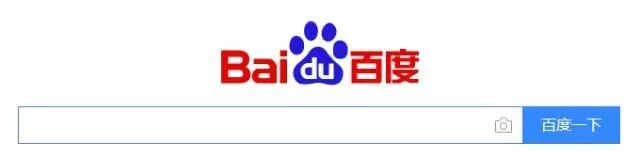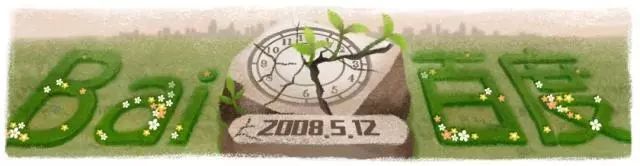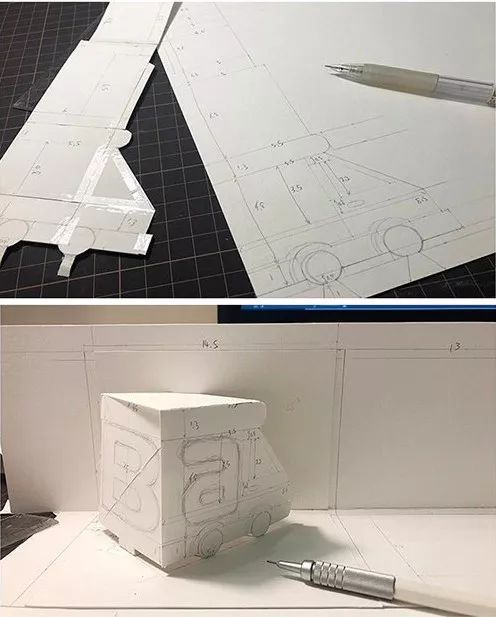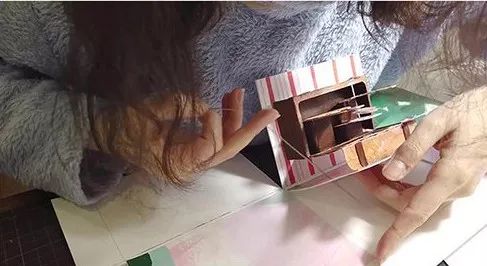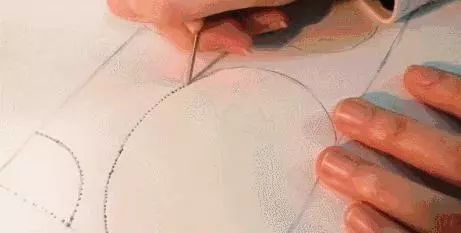
不要只盯着谷歌,百度的Doodle,同样精彩!
不要只盯着谷歌Doodle看,
多关注一下百度,
百度Doodle同样精彩!
说起谷歌,必须要说到谷歌Doodle。每到特定的日子,五花八门的Doodle总是能成为人们津津乐道的话题。
Doodle用动画的方式,各种形式串联,简单通俗来表达,谷歌作为搜索引擎存在的意义。趣味横生,已融入了生活中的方方面面。
但是对于中国网民来说,最常接触到的,其实是百度。每次打开搜索引擎的时候,你有没有留心观察过百度Doodle?下面小编带您挖掘百度有趣的Doodle和这些Doodle背后的故事~
精彩的百度Doodle
平时打开百度首页,都能看到这个熟悉的红蓝标:
也许你早有发现,在一些特别的日子里,经典的红蓝标志也会变身为各式各样的 Doodle!
下面我们一起来看看,在最近两年,百度都换过哪些好看的“新衣服”:
▲2018日全食
▲2018情人节
▲2018春节
▲2018妇女节
▲2018汉语大字典
▲2018地球一小时
▲2018清明节
▲2018世界地球日
▲2018汶川地震纪念
▲2018中继星
▲2018文化和自然遗产日:榫卯的秘密
▲2018世界第一个表情符号诞生日
▲2018珠算日
▲2018冬至
▲2018圣诞节
▲2018父亲节
▲2019端午节
▲2019母亲节
▲2019全国爱眼日
▲2019妇女节
▲2019国际博物馆日
▲2019金庸诞辰日
▲2019JAVA语言诞生日
今年最引人注目的,就是情人节那趣味性十足的Doodle:
▲2019情人节
这个Doodle的制作过程,非常地用心。先在白纸上画好建模图:
将建模图裁剪后粘贴到模型的物料上,作为裁剪和粘贴的参考,然后对物料进行裁剪折叠:
裁剪,最后粘贴拼装成立体情书:
然后是细致的上色过程:
最后进行组装和调试,不满意的细节再进行修改:
正是因为设计师对细节的精益求精,才有了情人节可爱又富有细节的Doodle。
另外,去年好几个Doodle都是设计师手作的。
制作这些Doodle的花絮,可以看看下面这个短视频:
原来,Doodle上看到的每一个精致的图案,其实都是设计师们自己手工建模、雕刻出来的:
有特殊需要的时候,心灵手巧的设计师们还会用彩泥捏出原型!
然后进行烘焙、等到彩泥干燥之后摆好造型:
最后,设计师们用后期技术对图像进行“加工”,一个可爱的Doodle就这样完成了!
看了这些Doodle的制作过程,小编觉得,原来设计师不仅要会用软件,还得会手工呀!是设计师的精雕细琢,才有了百度许多可爱的Doodle。不要只盯着谷歌Doodle看,多关注一下百度,百度Doodle同样精彩!